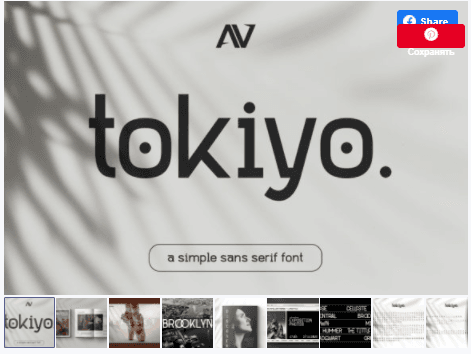
Tokiyo Font
Tokiyo — классный, минималистичный и современный дисплейный шрифт. Он идеально подходит для написания веб-дизайна, визитных карточек и всего остального, что требует уникального подхода.